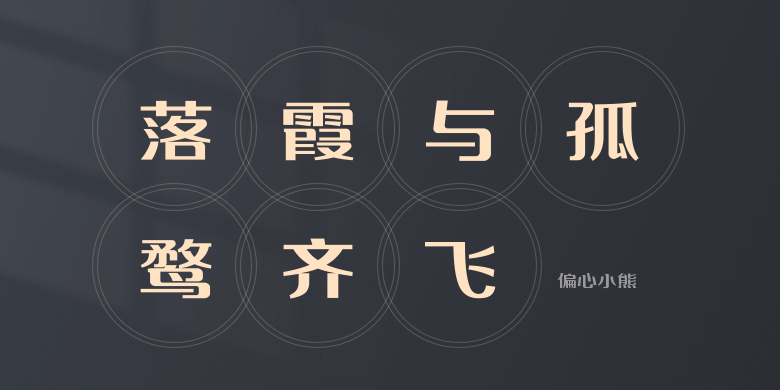
偏心小熊
偏心小熊,这款字体结构工整、笔画清晰,兼顾美观与易读性,适用于标题、正文、海报、包装、LOGO 等多种场景。字形优雅稳定,风格百搭耐看,适配日常排版与创意设计,让文字呈现更舒适、更具质感。偏心小熊一笔一画,皆是细节,以均衡的比例、流畅的线条打造舒适视觉体验,字形端正大气,风格简约现代。无论是商业设计、品牌宣传还是日常排版,都能轻松驾驭,让文字更有格调与力量。偏心小熊字体下载。